LOGO对于企业、品牌的都起到识别和推广作用,选择的字体更是至关重要的环节。一张醒目具有视觉冲击力的图片字体 可以快速达到让消费者记住的宣传效果。很多行业为了直观的达到这一效果,直接使用字体logo设计 ,简单直观。小编今天要给大家推荐的就是几款适用于logo设计的字体,咱们一起来看看吧。
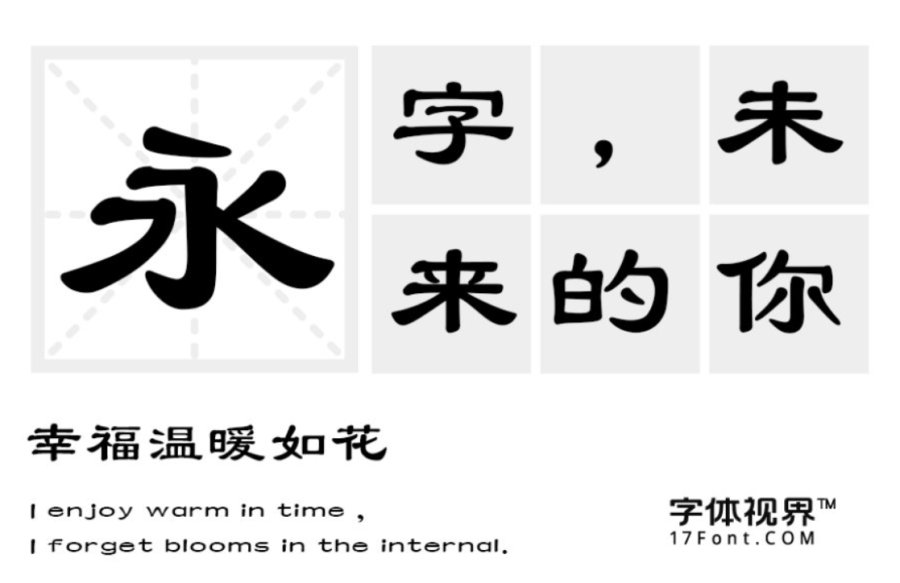
三极隶书简体:这款字体以传统的隶书结构和笔芯特征为根本来扩充,笔画横长竖短,平稳均匀,字形轮廓统一,收放自如。不仅适用于logo设计,用于杂志书刊、标题、包装设计等方面都很适用。
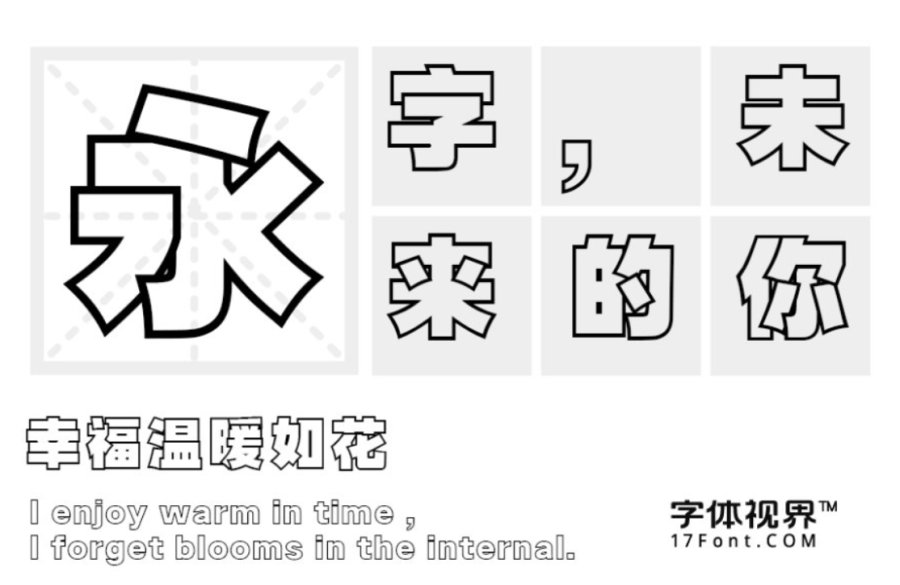
三极空叠体:这款字体用笔画叠加的形式展现出字体的风格,布白均匀、重心一致。字形清新,结构严谨,作为logo设计视觉体验极佳,用于各类屏幕显示、印刷与广告设计都能达到很好的展现效果。
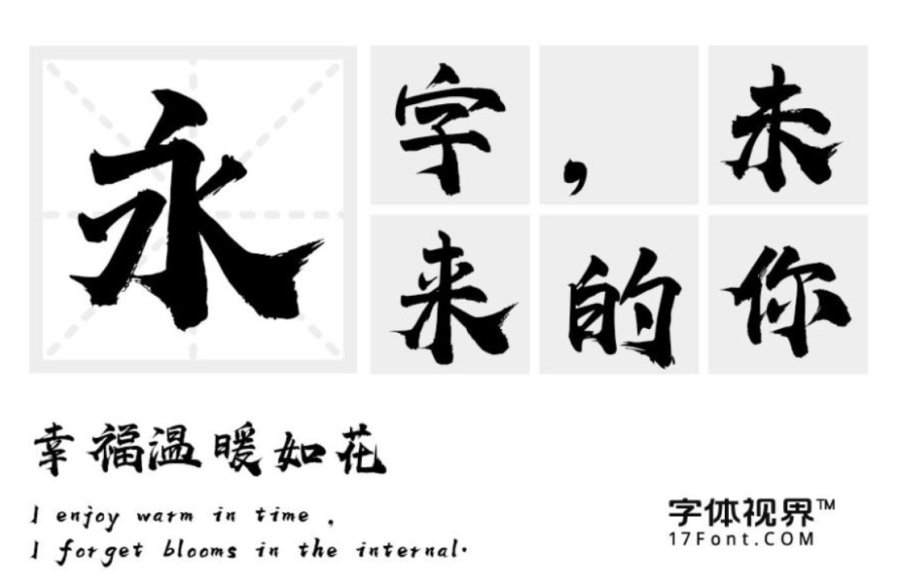
上首华凤书法:这款字体的风格给人的感觉很稳重,字形结构偏方块形,笔画细节处理坚硬有力、具有浓郁的现代感,字形清晰不仅看图片识别字体 简易,还有很强的视觉记忆点。